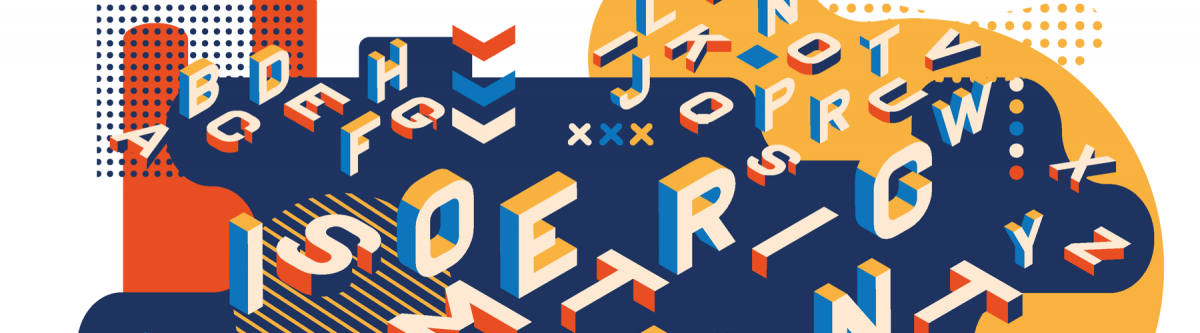
Estás diseñando un póster, flyer o folleto? Estamos seguros de que ya habrás pensado en la mayoría de elementos que necesitas considerar, como el mensaje que quieres transmitir, los colores que vas a usar, donde colocarás tu logotipo etc. Todos estos aspectos son muy importantes para garantizar un resultado efectivo. Pero hay un elemento que muchas veces es ignorado: La tipografía.
Cuando hablamos, nuestras expresiones, gestos y postura juegan un papel importante en el mensaje que vamos a transmitir. Pero esto cambia a la hora de escribir, las palabras sólo son palabras, verdad? No es del todo así. Cuando hablamos del mensaje escrito hay un aspecto que juega el mismo rol que los gestos que usamos al hablar: La tipografía. Cada tipografía tiene la habilidad de añadir una emoción diferente al texto.
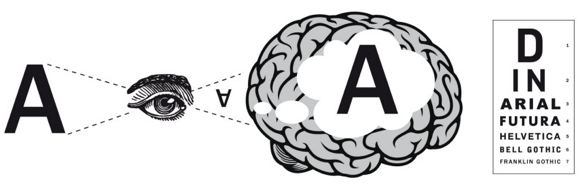
Para explicar este fenómeno se han llevado a cabo varios estudios. Cuando miramos el texto, nuestros ojos siguen las líneas. Esto hace que leer se convierta en una experiencia física. Se puede comparar a la forma que reaccionamos con el lenguaje corporal. En una encuesta realizada por Poffenberger y Barrows en 1933, se pidió relacionar emociones con diferentes tipos de formas. Las líneas descendentes eran consideradas tristes, mientras que las ascendentes daban sensación de alegría a los participantes del estudio.
Aunque no lo creas, todo tipo de emociones se pueden representar con la tipografía. Un grupo de psicólogos hicieron leer a más de cien estudiantes en Nueva York un artículo satírico del New York Times. A parte del grupo se le dejó leer el artículo en Arial y al resto en Times New Roman. Más tarde, se llegó a la conclusión que Times New Roman era una tipografía más apropiada para un artículo satírico, pues tenía un aspecto más divertido y enfadado. Así que vemos que la tipografía refleja emociones que normalmente expresamos con gestos y expresiones faciales. Nuestras caras se redondean cuando sonreímos, lo cual hace que la tipografía de forma redondeada nos transmita esta emoción. También podemos observar este aspecto en la caligrafía. Cuando tenemos prisa, tendemos a escribir en cursiva, y cuando estamos enfadados, de forma más marcada. Intenta hacer el cuestionario de arriba y reflexiona sobre qué tipografía muestra mejor cada emoción. Así es como las personas que rellenaron el cuestionario se dieron cuenta de que tipografía representaba las emociones del mejor modo. Hay algunas que no son del todo evidentes, pero otras realmente lo son, sobre todo la emoción “calmado”.
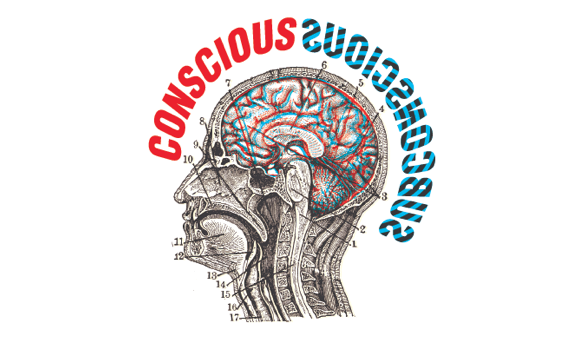
Esta información puede resultar de especial interés a los profesionales del marketing, así como también a los diseñadores gráficos. Una vez estableces el objetivo de tu campaña de marketing o diseño, y ya sabes qué emociones quieres transmitir a tus clientes, cómo les quieres hacer sentir, puedes elegir la tipografía adecuada para lograrlo.